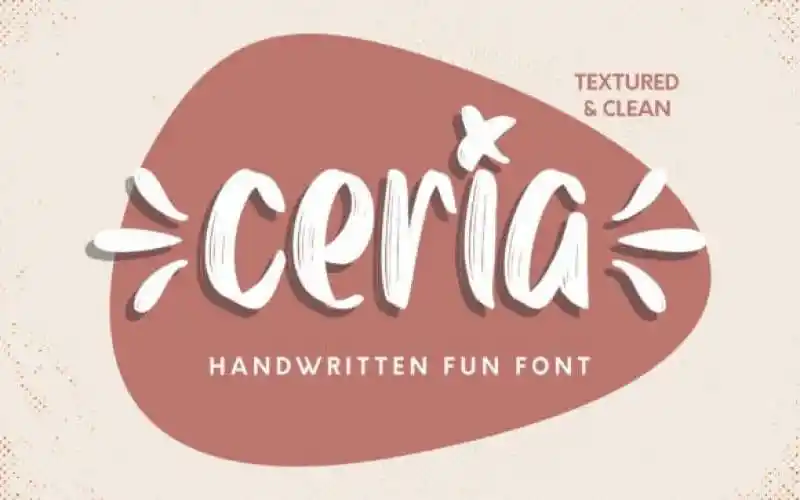
Ceria Script Font – Fonte Grátis
Ceria Script Font
A Ceria Script Font é uma nova opção para seus projetos digitais, uma fonte escrita a mão em formato brush com personalidade atraente e perfeitamente suave. Cada traço está cuidadosamente pensado, garantindo um acabamento elegante e fluido que se move bem entre seu trabalho de cabeçalho e corpo do texto. Designada pelo designer Hamilton, esta fonte é uma mistura perfeita entre a elegância da caligrafia tradicional e a sensação contemporânea e atualizada. Seja para gráficos de nível elevado ou criações simples, Ceria trará vida aos seus projetos e garantirá que eles se destacam da multidão. Com sua base variável e linhas suaves, esta fonte oferece uma variedade impressionante de caracteres e alternativas de letra, além de seu estilo elegante que mantém uma conexão com a caligrafia enquanto parece moderna e vibrante. Experimente Ceria e veja como ela pode transformar o visual dos seus projetos em algo realmente único e sofisticado.